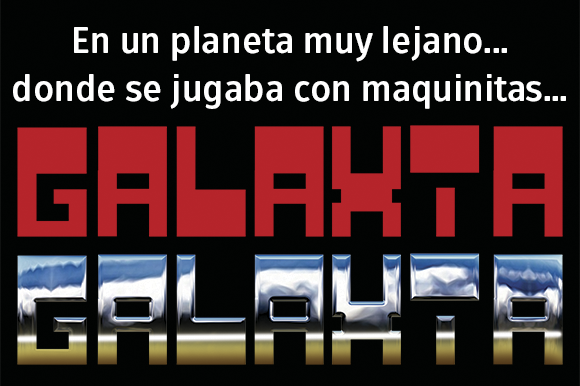
Font name: | Galaxia |
Author: | Grafito Design |
Note by Grafito Design | |
Esta fuente recuerda a las maquinitas (tragaperras) y a los juegos como g�laga |